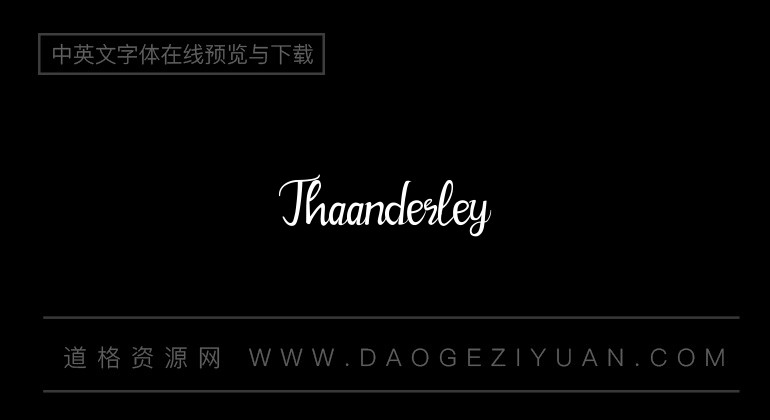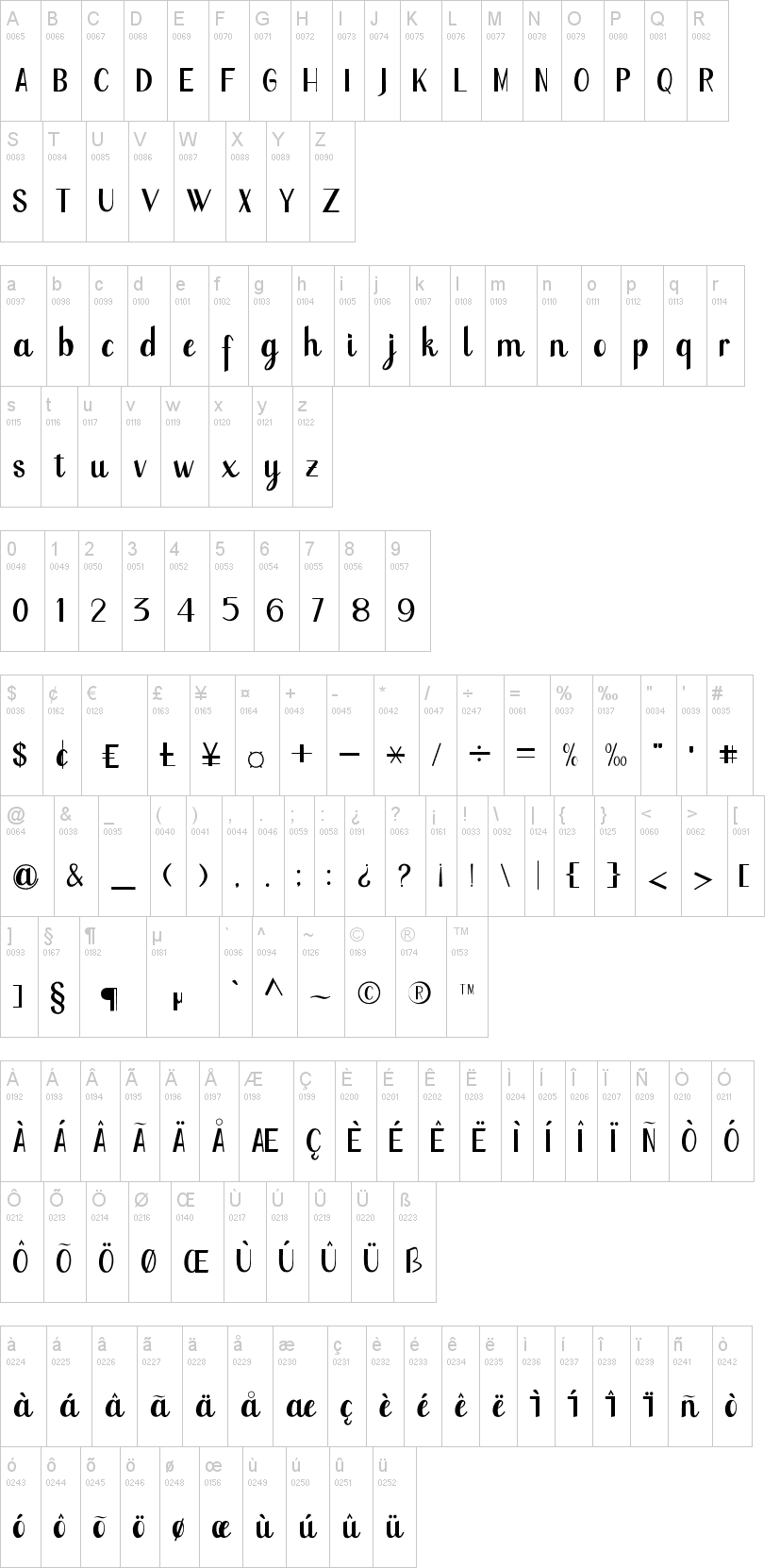
Thaanderley
Thaanderley 字体是一种现代风格的字体,它由设计师 Agni Ardi Rein Prasetyo 创造。这种字体非常适合用于标题、标志、海报和其他设计项目,它的风格非常独特,具有一定的艺术性。 Thaanderley 字体的特点包括: 1. 独特的字母形状:Thaanderley 字体的字母形状非常独特,有时候甚至让人感到有些艺术化。 2. 现代风格:该字体设计时注重现代感,适合用于现代设计项目,比如网站、移动应用等。 3. 多种字重:Thaanderley 字体有多种字重可供选择,可以满足不同设计需求。 总的来说,Thaanderley 字体是一种独特而现代的字体,适合用于各种设计项目,能够为设计师带来新的创意和灵感。
Thaanderley是一款非常不错的手写艺术字体,具有很好的视觉感,适合于文化类的宣传设计、商业类品牌的广告和产品包装设计以及个性化文字排版等较多场景。